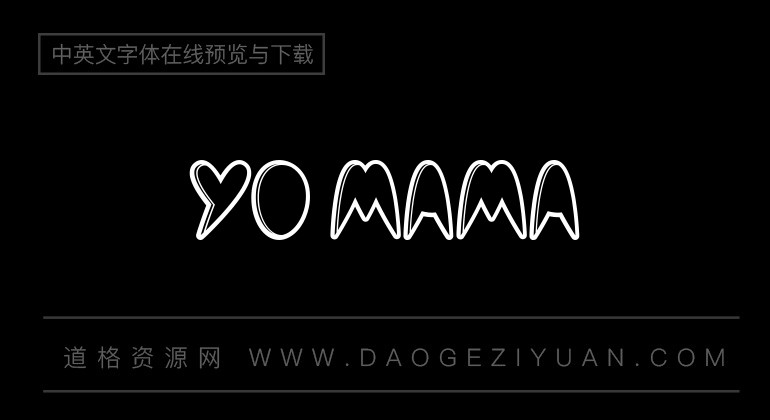
Yo mama 字体是一种具有活力和趣味的涂鸦字体,它是由英国设计师 Matt W Moore 创作的。它的字体风格充满了活力,有着抽象的笔触,更多的是表达艺术家的想象力和创意。它的字体有着抽象的涂鸦风格,且有着多种多样的字体设计,可以满足不同设计师的需求。内容介绍
Yo mama是一款非常不错的手写艺术字体,具有很好的视觉感,适合于文化类的宣传设计、商业类品牌的广告和产品包装设计以及个性化文字排版等较多场景。